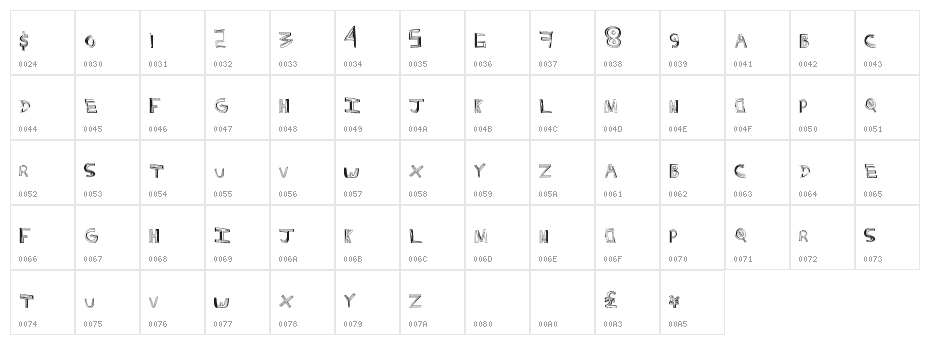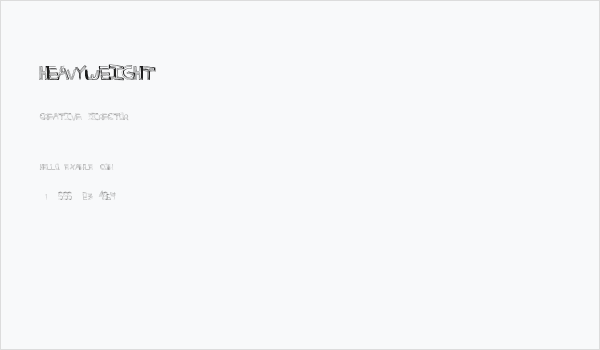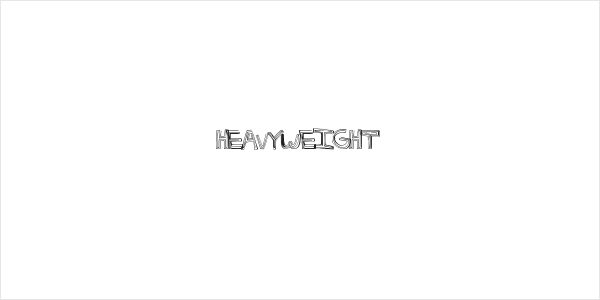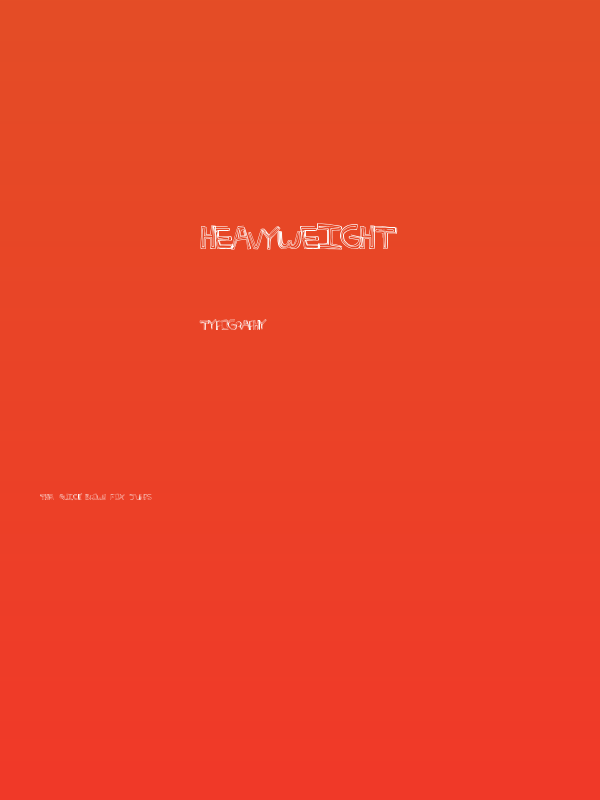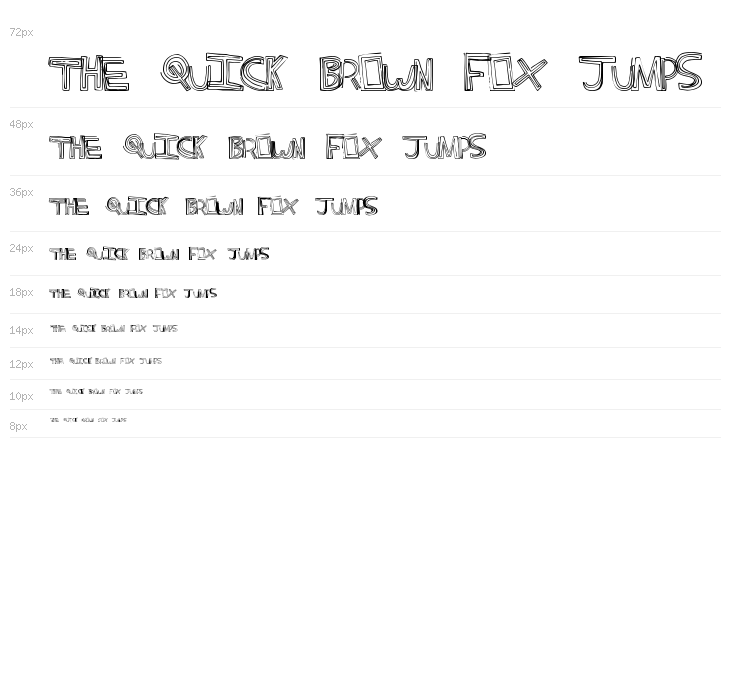
HeavyWeight Font
| Estilo general | Playful, Artistic, Energetic |
| Caso de uso | Headlines, Posters, Creative Projects |
| Proyectos propuestos | Ideal for posters, children's books, creative branding, and playful graphic designs. |